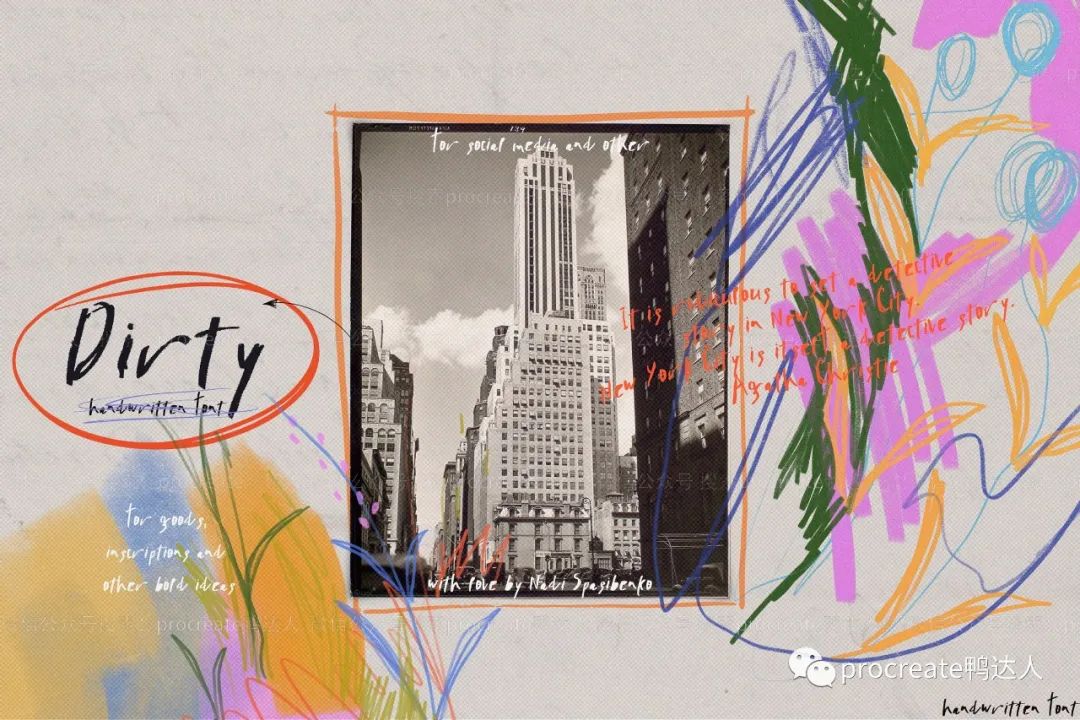
童趣随性手写字体也太用了,画面瞬间“动”起来了【751期】
一款儿童随性涂鸦、手绘效果的文字装饰、字体和图形字体集合素材包,线条模拟漫不经心的信手涂鸦、乱涂乱抹、抽象图形等等,有一种放荡不羁的叛逆感。素材总共有:2个WOFF格式的文件、2个OTF格式的文件。内容很多,如:英文大小写字母、数字、线条、几何图形、花等,您可以单独使用,也可以随意组合运用。适用于潮流、街头、快时尚、设计品牌的产品包装、服装印花、宣传海报等。